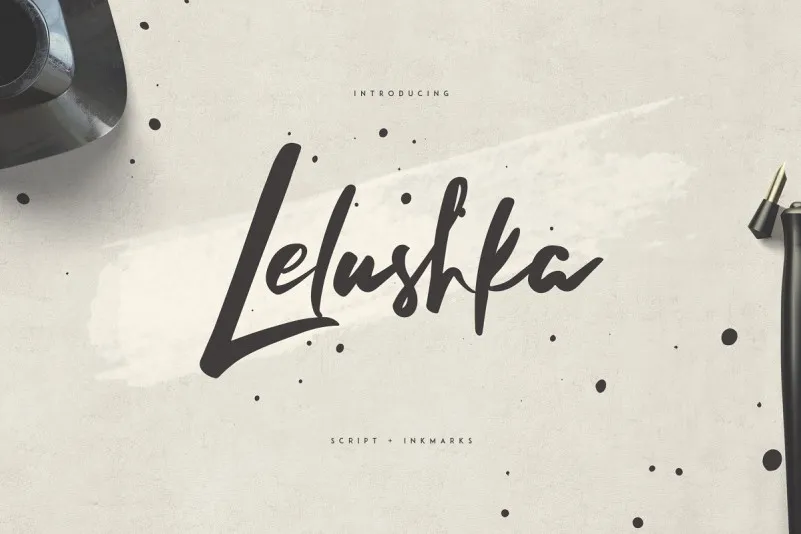
Lelushka Script Font – Download Grátis
Lelushka é uma linda fonte script inspirada na tipografia à mão livre e no estilo brush. Inspirada por suas 20 formas de tinta, ela oferece um toque urbano e grunge que adiciona uma pitada única a qualquer projeto de design. Este font está disponível em várias línguas e é perfeitamente adaptável para se tornar parte do seu próximo design de marca ou até mesmo como um overlay elegante sobre qualquer imagem de fundo. Concebida e compartilhada pela VPcreativeshop, Lelushka é uma fonte versátil que funciona excelente tanto em grandes tamanhos quanto em designs menores. Ideal para branding projetos, designs para casa, embalagens de produtos ou até mesmo como cabeçalho em revistas. Este script vem com um toque único e personalizado, tornando-o perfeito não apenas para textos simples, mas também para estilos mais elaborados e criativos.